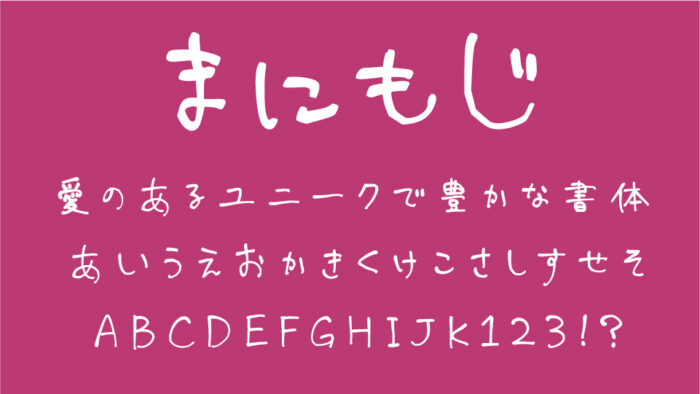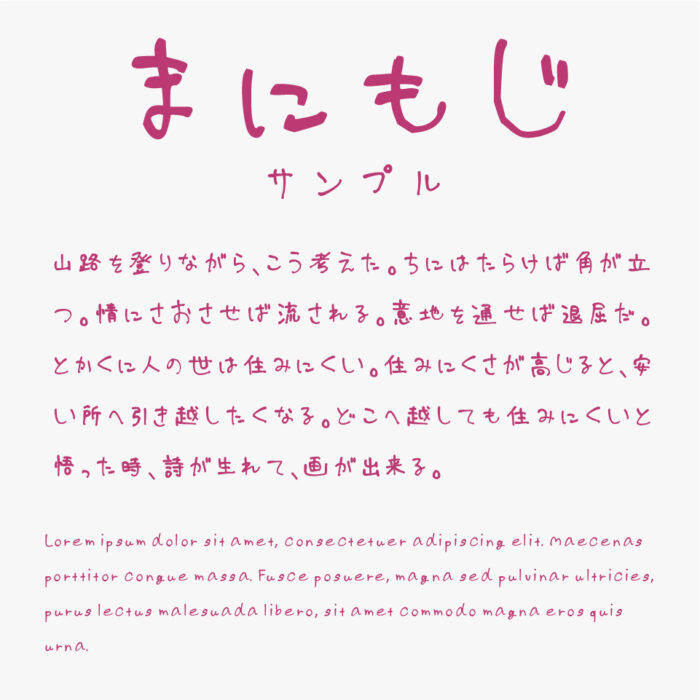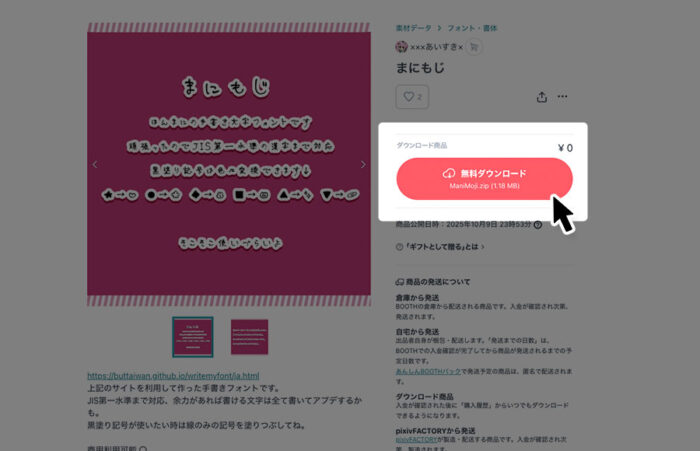
まにもじフォント
まにもじフォントは、こぶりに作られてた丸みのあるゆったり感が魅力の手書きフォントです。
線の太さにやさしい強弱があり、平仮名・カタカナのどれもが軽やかで、まるで気の置けない手紙を読むような親近感のある手書き文字となっています。角が丸く、空気を含んだような間の取り方で、読む人の気持ちもふわりと和らぎます。